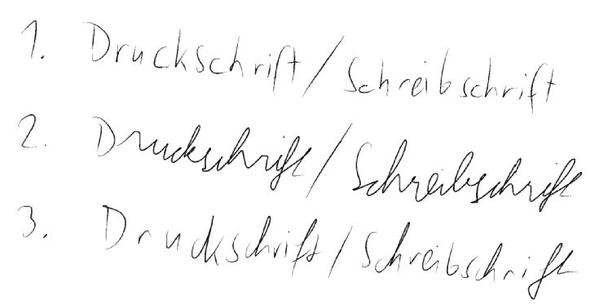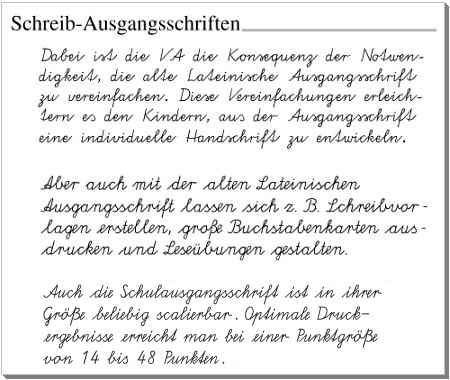
26 Schreibschrift Schöne Schriftarten Word
Schreibschrift schöne schriftarten word. Schrift wechseln in word um in word eine andere schrift zu nutzen wählt man diese in. Wir stellen eine kleine auswahl an schriftarten vor die sich kommerziell nutzen lassen und obendrein kostenlos sind. Durchsuchen sie nach alphabetischer reihenfolge stil autor oder popularität.
Fonts die wie von hand geschrieben aussehen wirken persönlich und wecken emotionen. 20 schöne schreibschrift free fonts für webdesigner. Undzwar suche ich eine schöne schriftart für word.
Undzwar suche ich eine schöne schriftart für word. 28 verschiedene handschrift schreibschrift schriftarten lade dieses bild aus canvas foto sammlung herunter handschriftliche schriftarten wirken persönlich und elegant hier sind 28 script fonts die du kostenlos nutzen kannst. Laden sie kostenlose schriftarten für windows und mac herunter.
Kalligraphie schriftarten frei zur kommerziellen nutzung. Der japanische designer präsentiert mit tangerine einen eleganten kalligraphie font der sich an schriften aus dem 16. Ich gestalte ein fotoalbum mit gedichten usw.